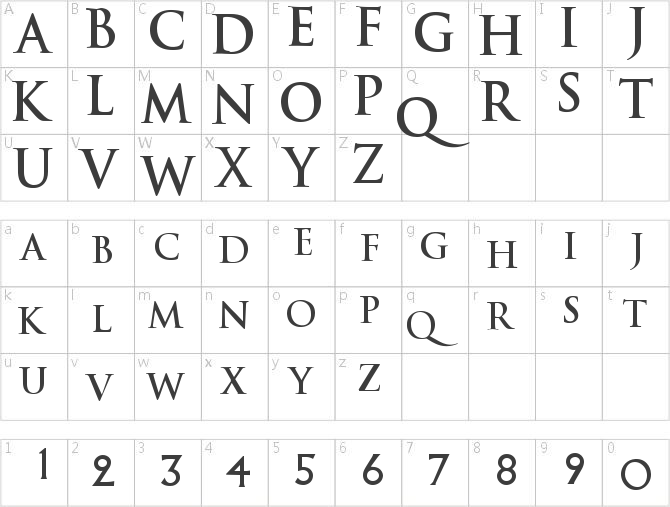
An Unfortunate Event DeWarped 詳情頁(yè)
An Unfortunate Event DeWarped字體字庫(kù)是一款讓人賞心悅目、百看不厭的英文字體,適合各類(lèi)廣告和產(chǎn)品包裝設(shè)計(jì)應(yīng)用,字體大小1.91MB,格式為ttf字體,上傳用戶(hù)是82年的拉菲,作者/版權(quán)方為未知